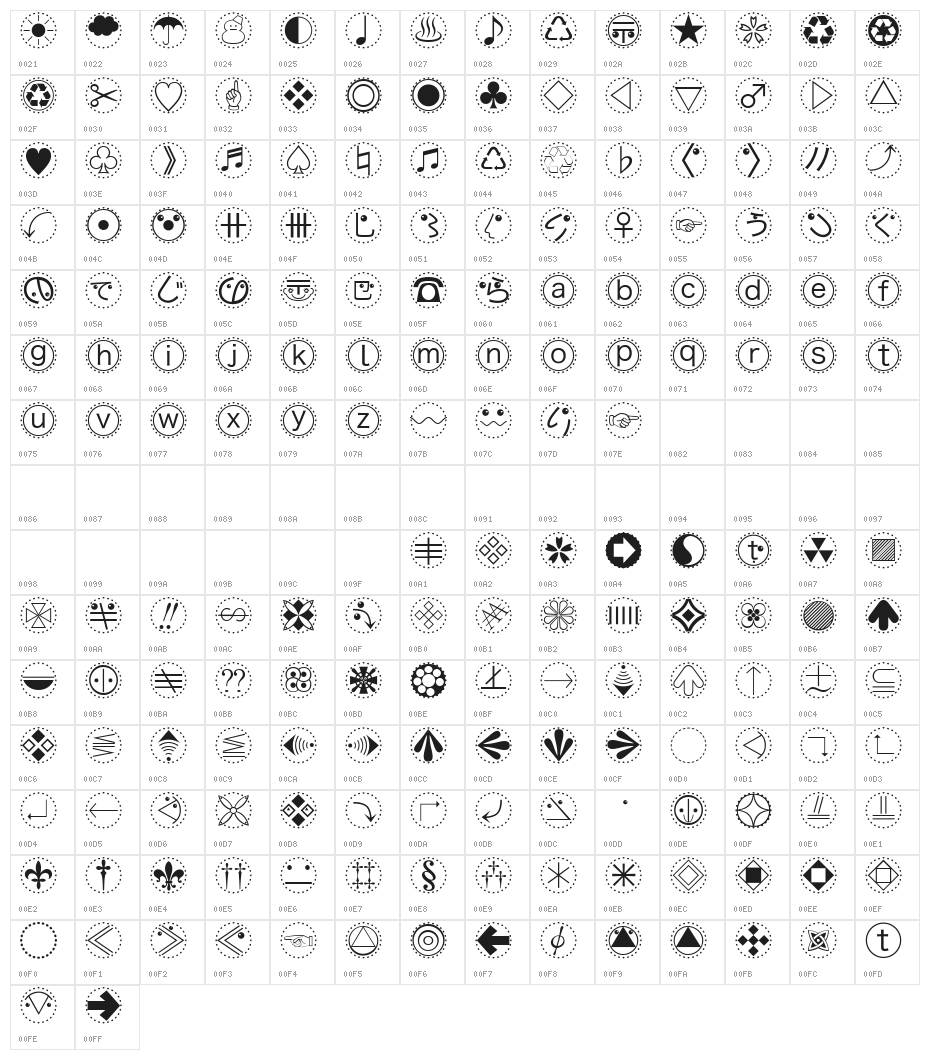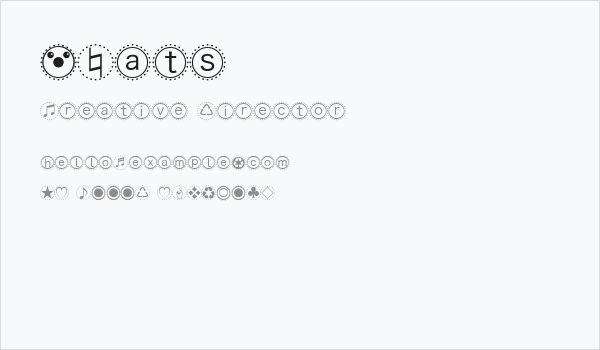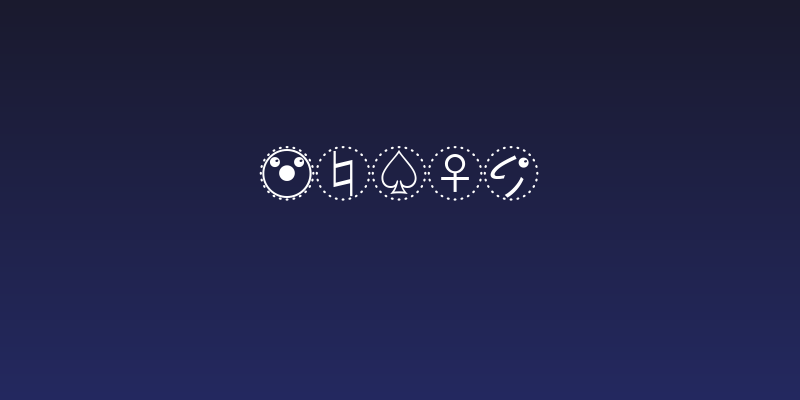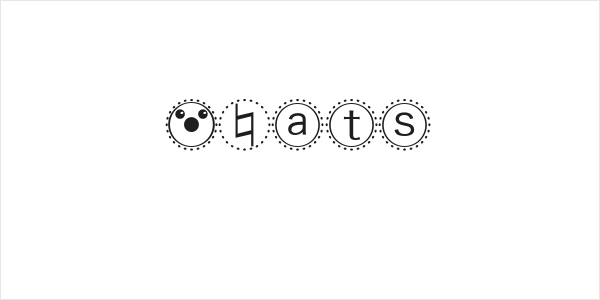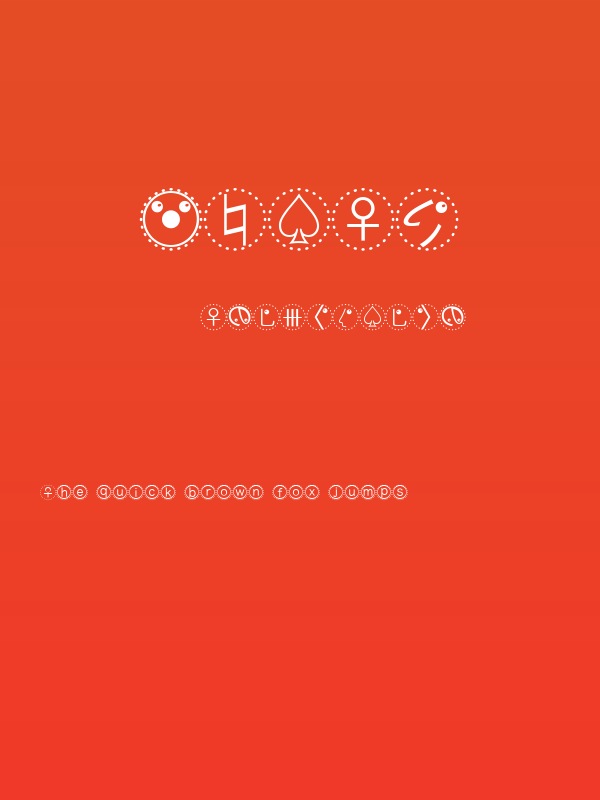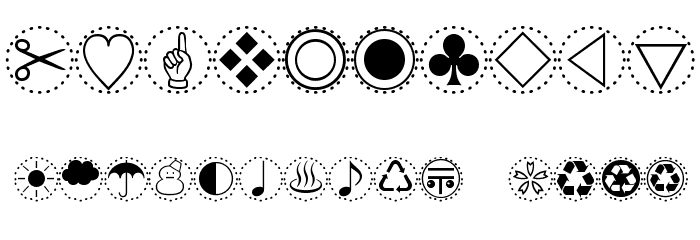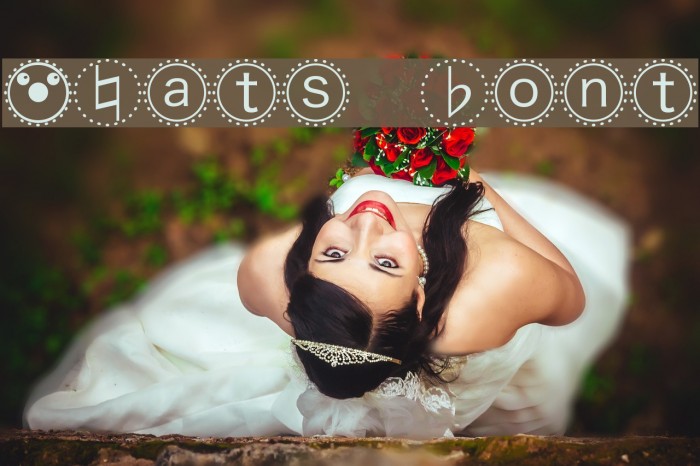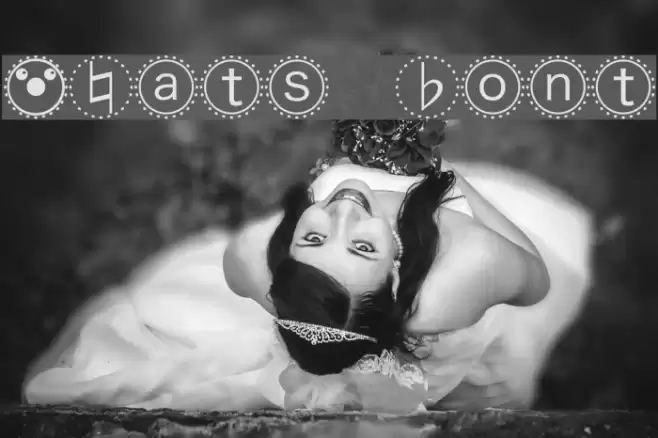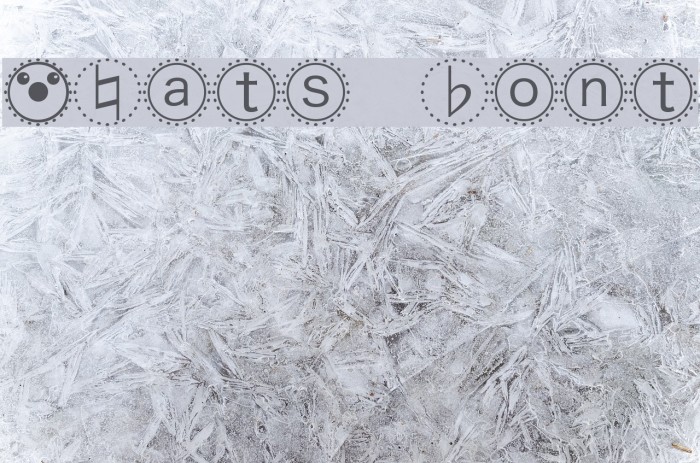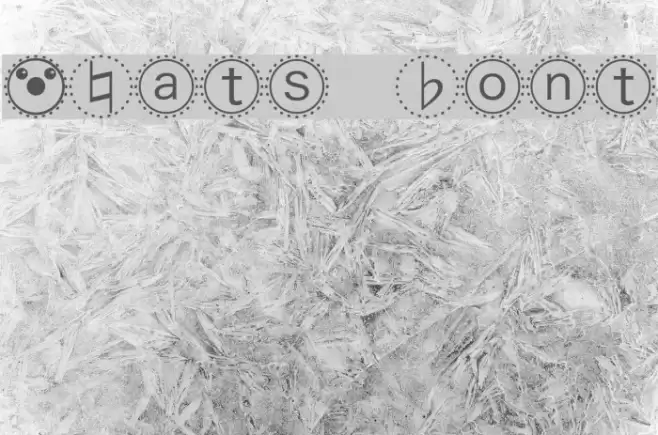
MBats Font
| Stil general | Playful, Whimsical |
| Caz de utilizare | Logos, Posters, Creative Projects |
| Proiecte propuse | Ideal for children's books, playful branding, creative posters, and educational materials. |